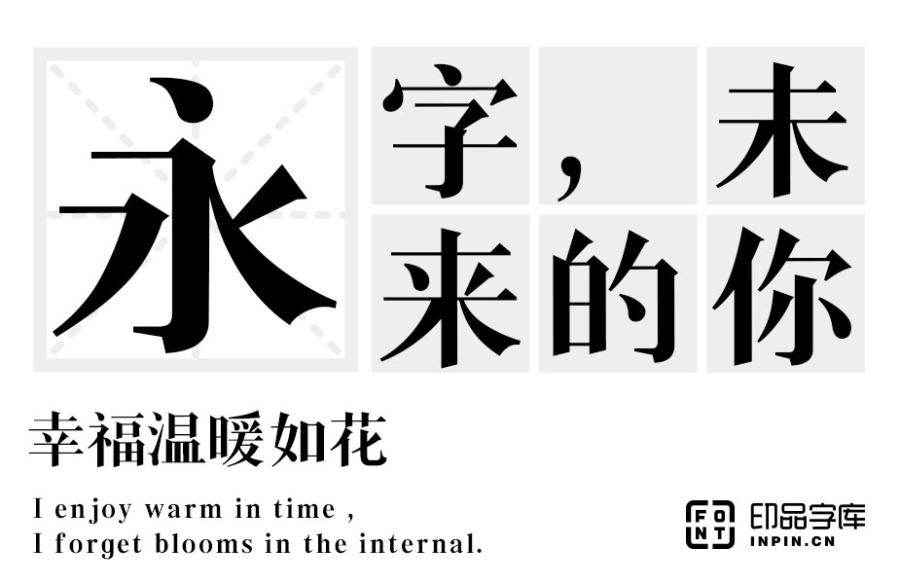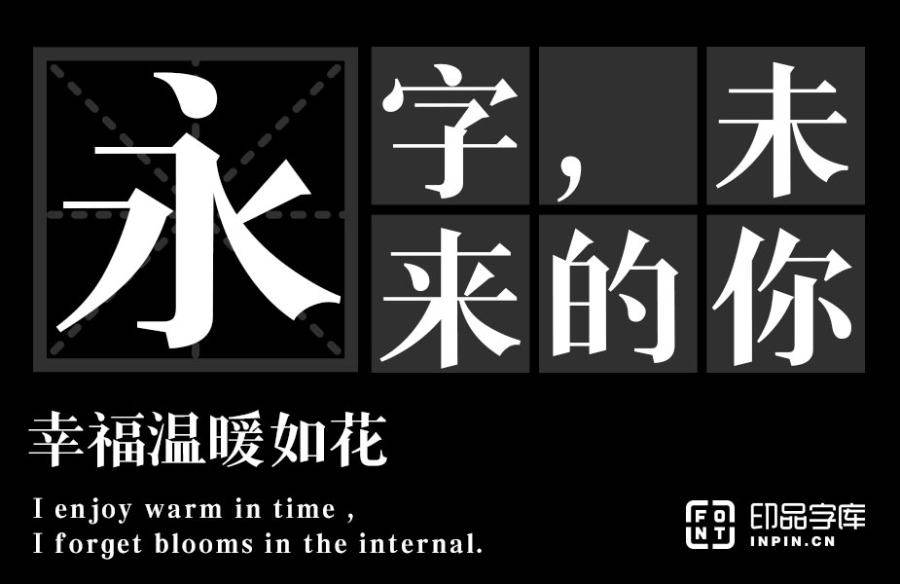
印品新字「印品小标宋简繁」小标宋-国家行政机关公文规定的一种标准字体
字体名称:印品小标宋简繁印品小标宋简繁
字体类别:宋体
适用场景:标题正文标志LOGO屏显宋体
字库简介:小标宋体是《国家行政机关公文格式》中规定的一种标准字体,主要用于政府文件中的发文机关标识、公文标题和主题词词目。印品小标宋简繁为了满足党政机关公文用字体的高要求而专门精修的字库产品,字体美观规范、清晰易读,完全保证电子公文共享交流时统一、准确、原版的完美显
印品小标宋简繁